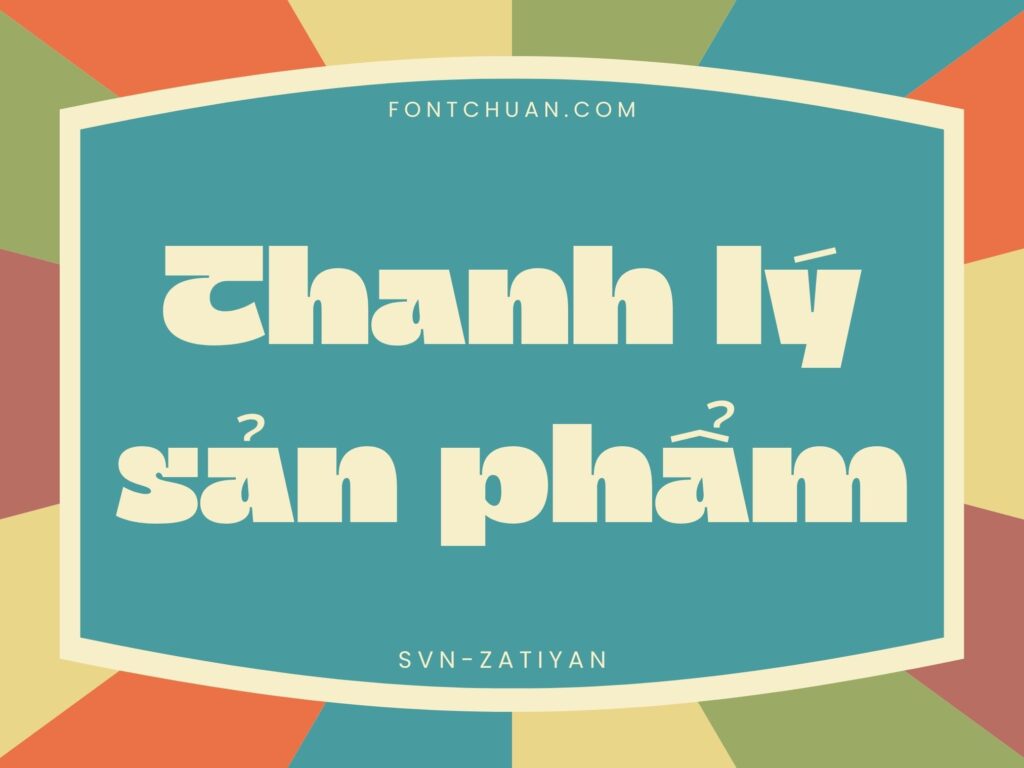
Font SVN Zatiyan Việt Hóa
Tác giả Font: Azzam Ridhamalik
Font SVN Zatiyan là phiên bản Việt hóa của kiểu chữ Zatiyan, được thực hiện bởi Styleno.1 Fonts. Zatiyan thuộc nhóm Font Decorative, là một kiểu chữ sans-serif đậm nét, kết hợp giữa phong cách hiện đại và cổ điển, tạo cảm giác mạnh mẽ và độc đáo. Font này được trang bị các ink traps giúp tăng cường khả năng đọc và mang lại phong cách nổi bật cho thiết kế, giúp tác phẩm của bạn dễ dàng thu hút sự chú ý.
SVN Zatiyan lý tưởng cho các dự án thiết kế logo, tiêu đề, bao bì sản phẩm và các ấn phẩm quảng cáo. Các ngành nghề như quảng cáo, công nghệ và bất động sản có thể tận dụng font này để tạo điểm nhấn trong thiết kế. Ngoài ra, font cũng phù hợp cho các sự kiện như Tết, Giáng sinh, Valentine và các lễ hội khác.